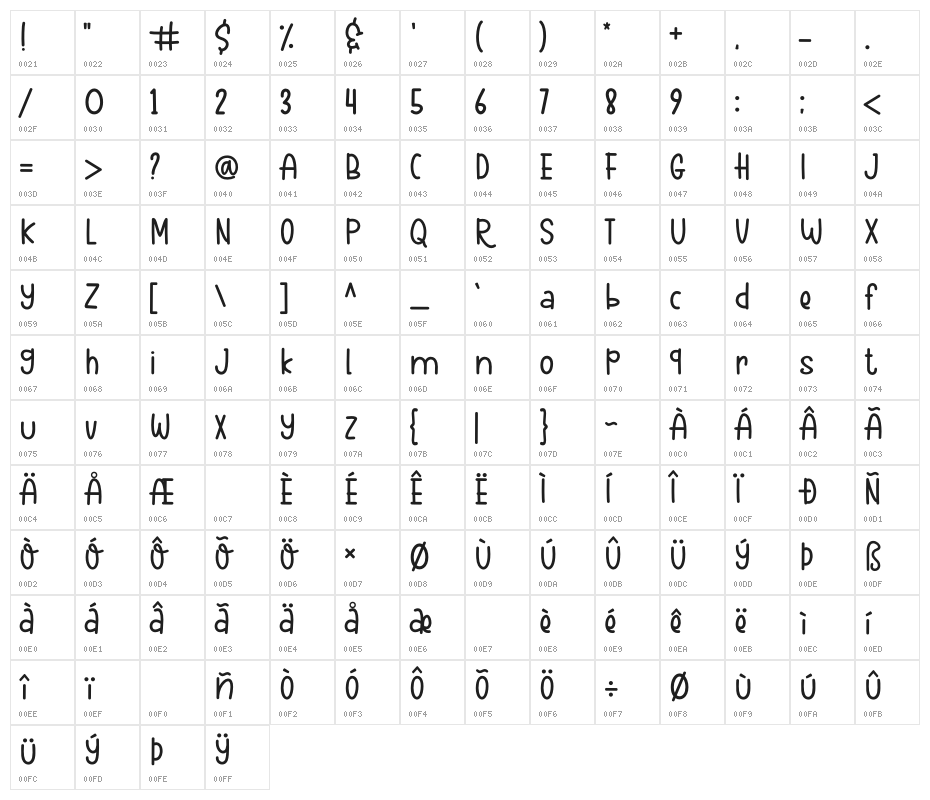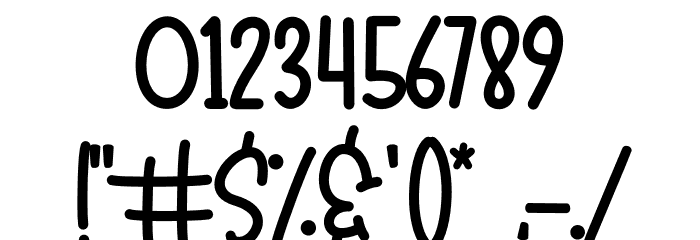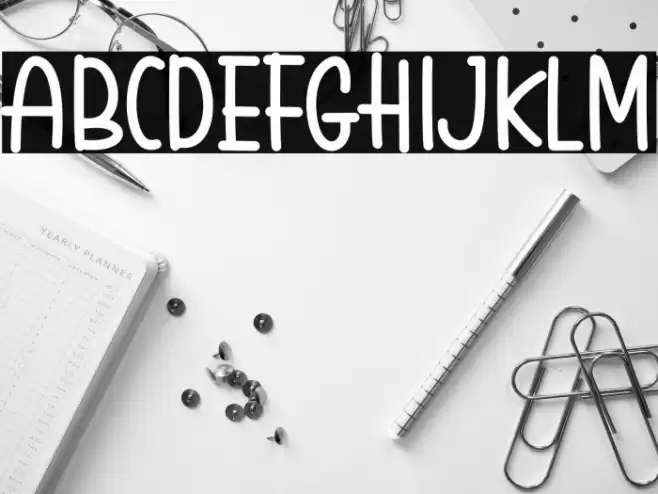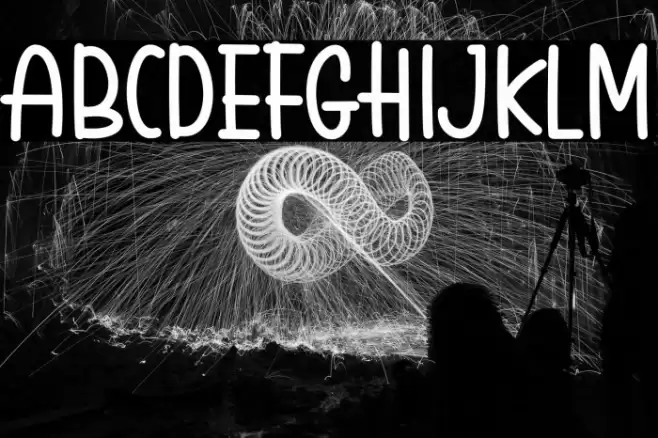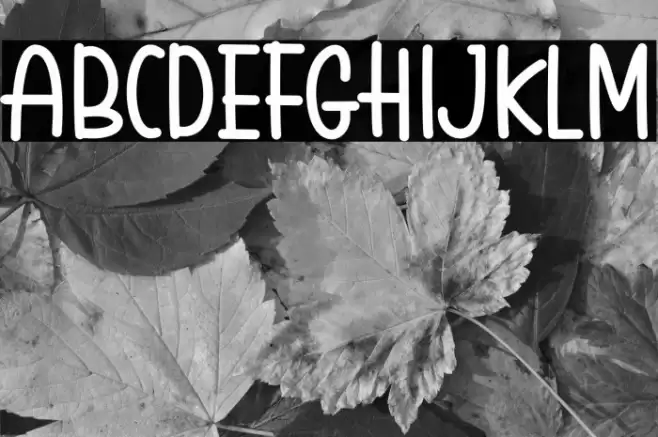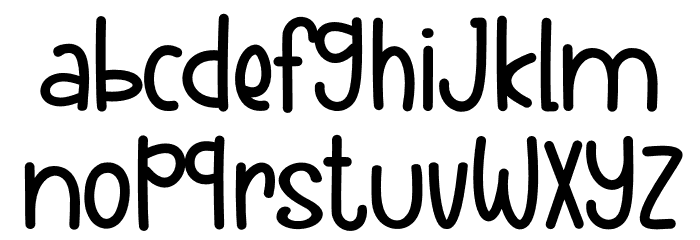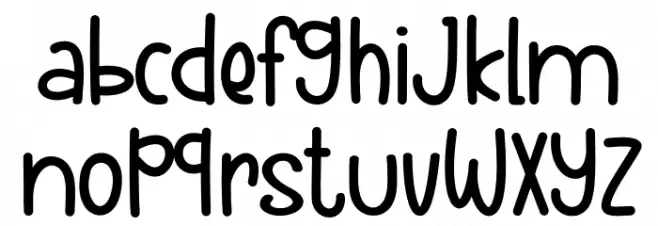
Holiday Island Font
Fonts by Willetter Studio
| النمط العام | Casual, Playful |
| حالة الاستخدام | Headlines, Logos, Informal Text |
| مشاريع مقترحة | Ideal for greeting cards, children's books, playful branding, and casual invitations. |